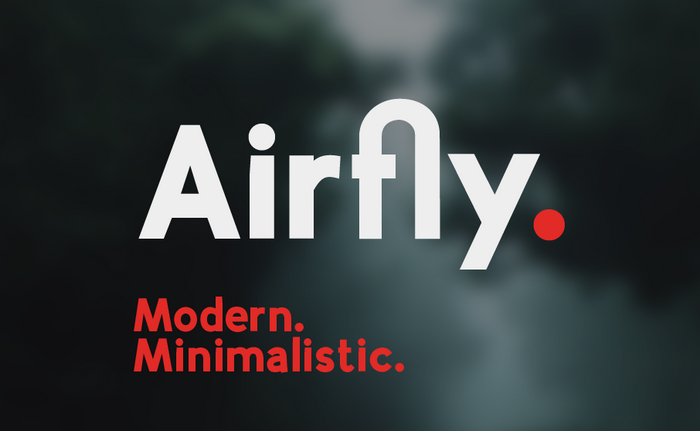
Airfly Typeface
Introduzimos a Airfly Typeface! Esta família de tipos foi criada pela Phitra-Design para aqueles que procuram uma fonte versátil e moderna. A Airfly é perfeita tanto para headlines quanto para blocos de texto, com um aspecto brilhante e linhas retas. Com seus ângulos aguçados e linhas retas, a Airfly vem em três estilos: Espinhento, Claro Leve e Regular, todos acompanhados de uma versão itálica. A sua característica mais chamativa é o modo discreto de apresentação que faz com que ela represente perfeitamente um tipoface equilibrado e suave. Não apenas oferece grande versatilidade para diferentes projetos gráficos, mas também garante um aspecto minimalista e sofisticado. Com a Airfly Typeface da Hamilton, você pode adicionar uma personalidade única à sua próxima criação visual.